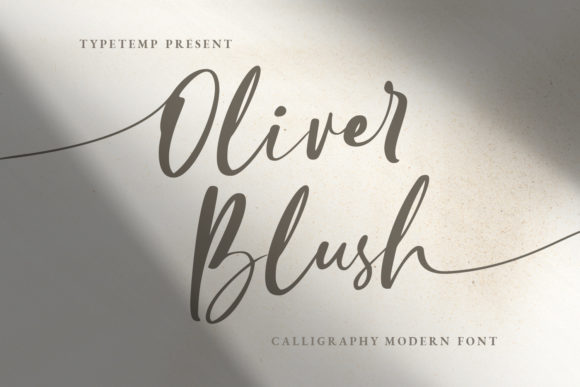
Oliver Blush
Oliver Blushのような高品質の素材をお探しの場合、このプレミアムパッケージはクリエイティブなプロジェクトに素晴らしい選択です。
精密に作られたOliver Blushは、クリーンなベクター、滑らかなタイポグラフィ、そして安心のための商用ライセンスを提供します。
POD(オンデマンド印刷)製品、結婚式の招待状、またはソーシャルメディアのグラフィックを作成している場合でも、Oliver Blushは理想的です。